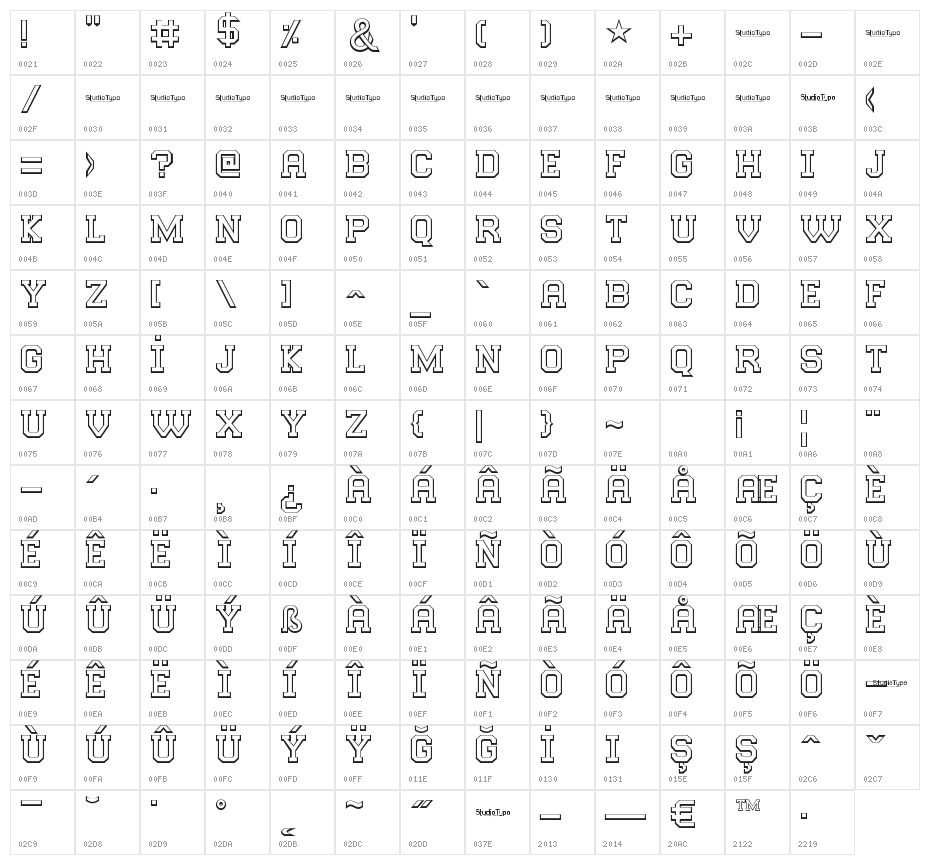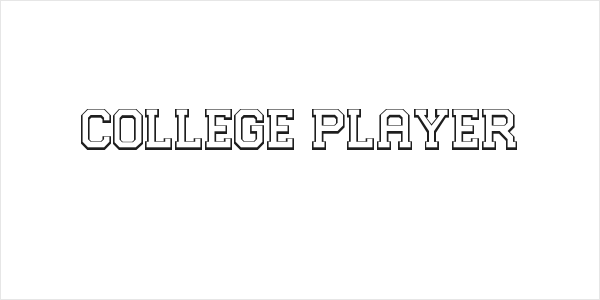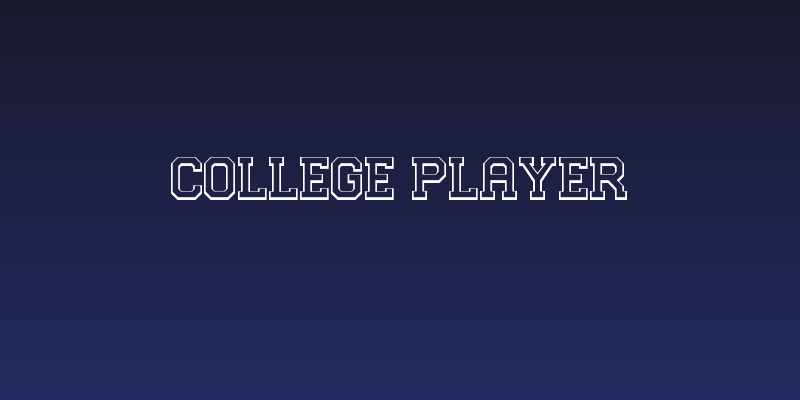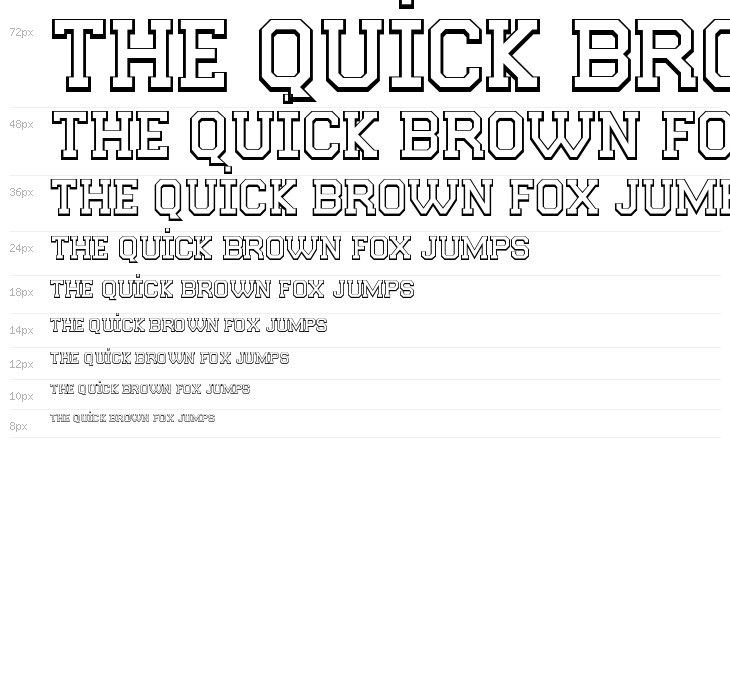
College Player Font
| Categorías | Old fashioned |
| Estilo general | Classic |
| Caso de uso | Logos, Headlines |
| Proyectos propuestos | Ideal for sports team branding, event posters, school spirit merchandise, and athletic apparel designs. |